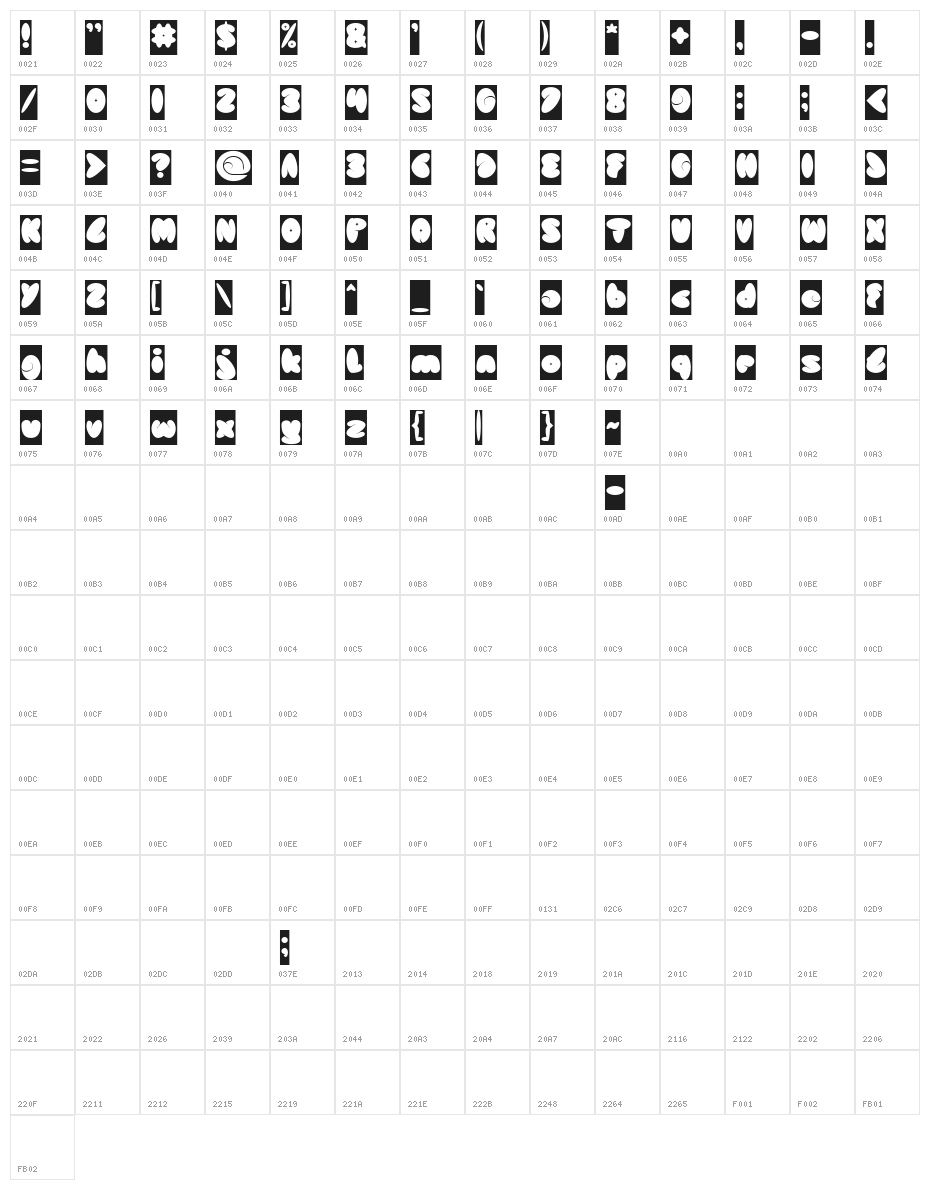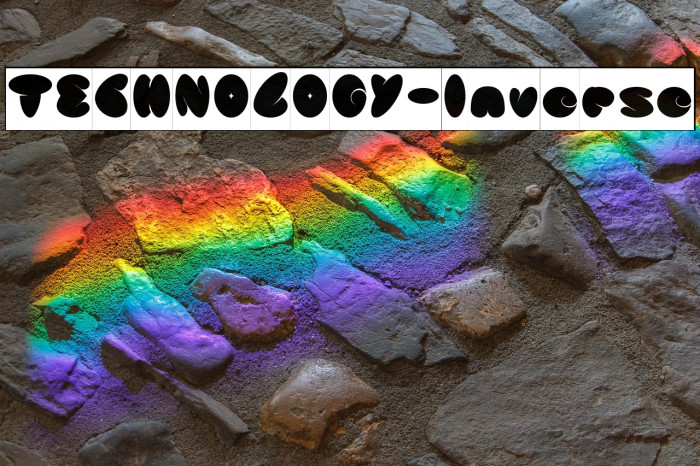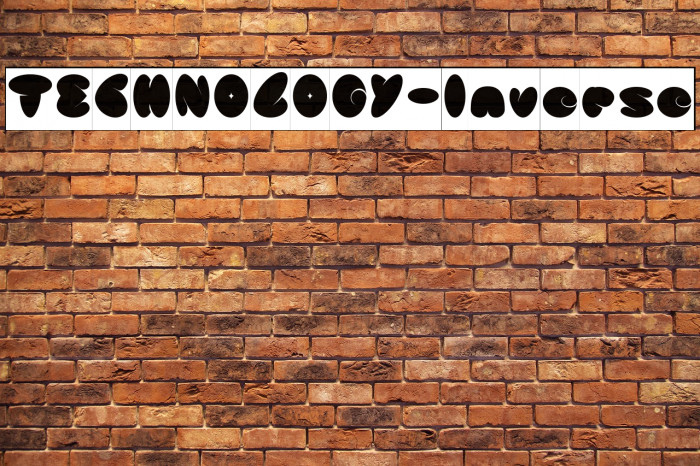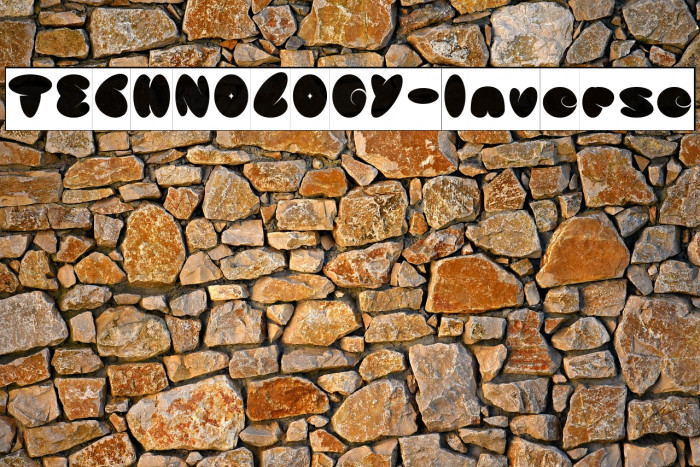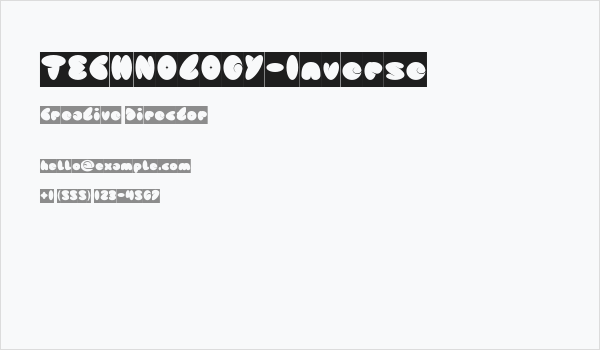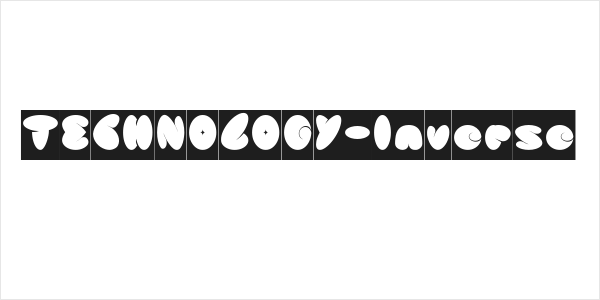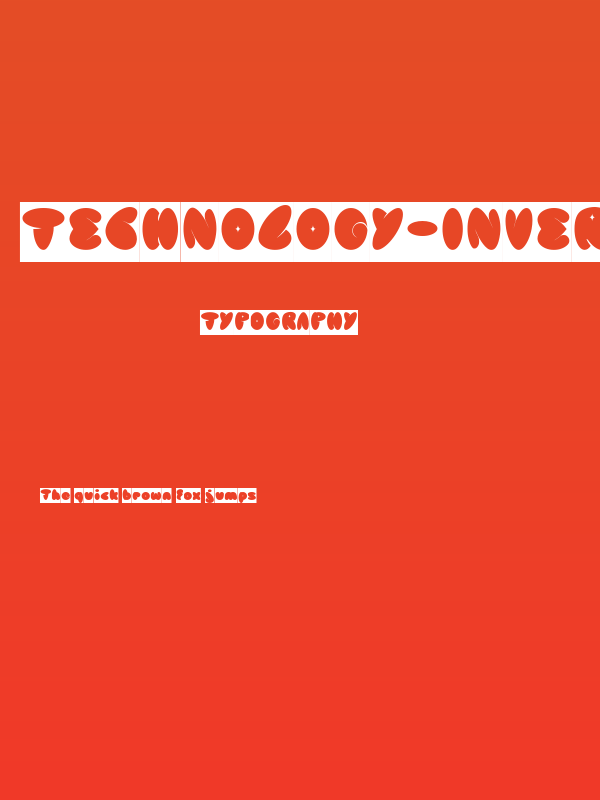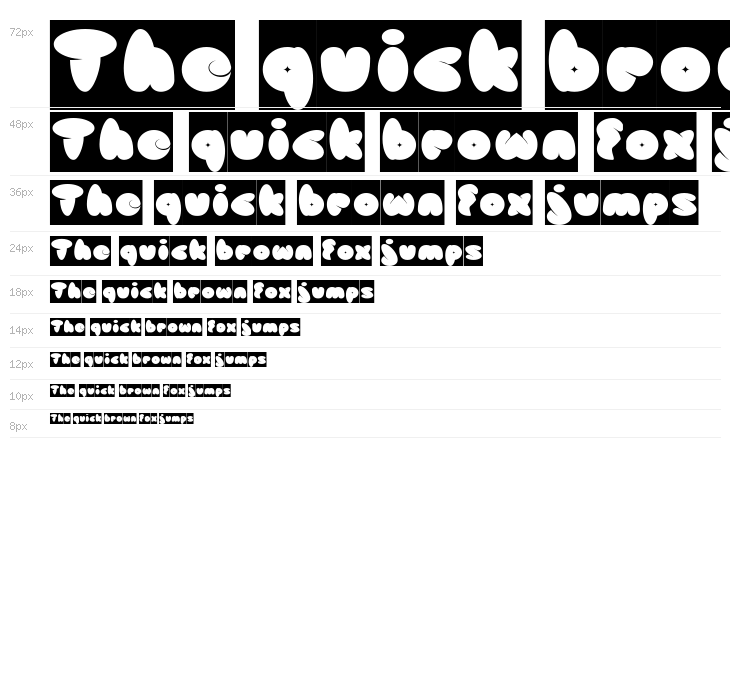
TECHNOLOGY-Inverse Font
| 全体的なスタイル | Playful, Whimsical |
| おすすめプロジェクト | Ideal for children's books, playful branding, party invitations, and creative posters. |